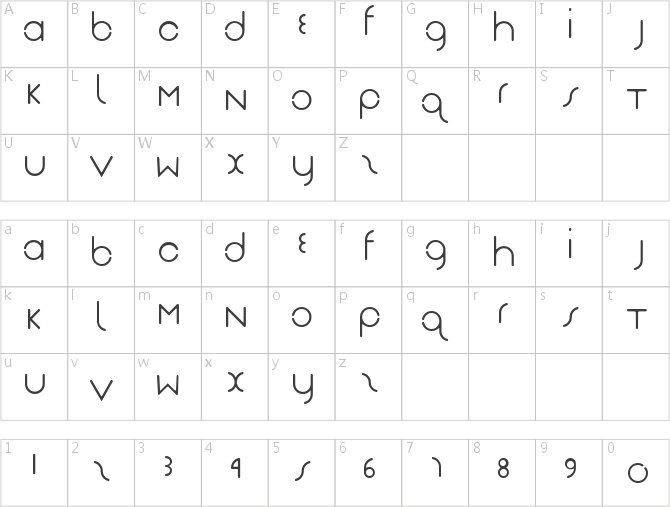
Das-Reicht-Gut-Regular
Das-Reicht-Gut-Regular介紹
Das-Reicht-Gut-Regular字體字庫是一款讓人賞心悅目、百看不厭的英文字體,適合各類廣告和產品包裝設計應用,字體大小0.02MB,格式為ttf字體,上傳用戶是手機洗相,作者/版權方為未知